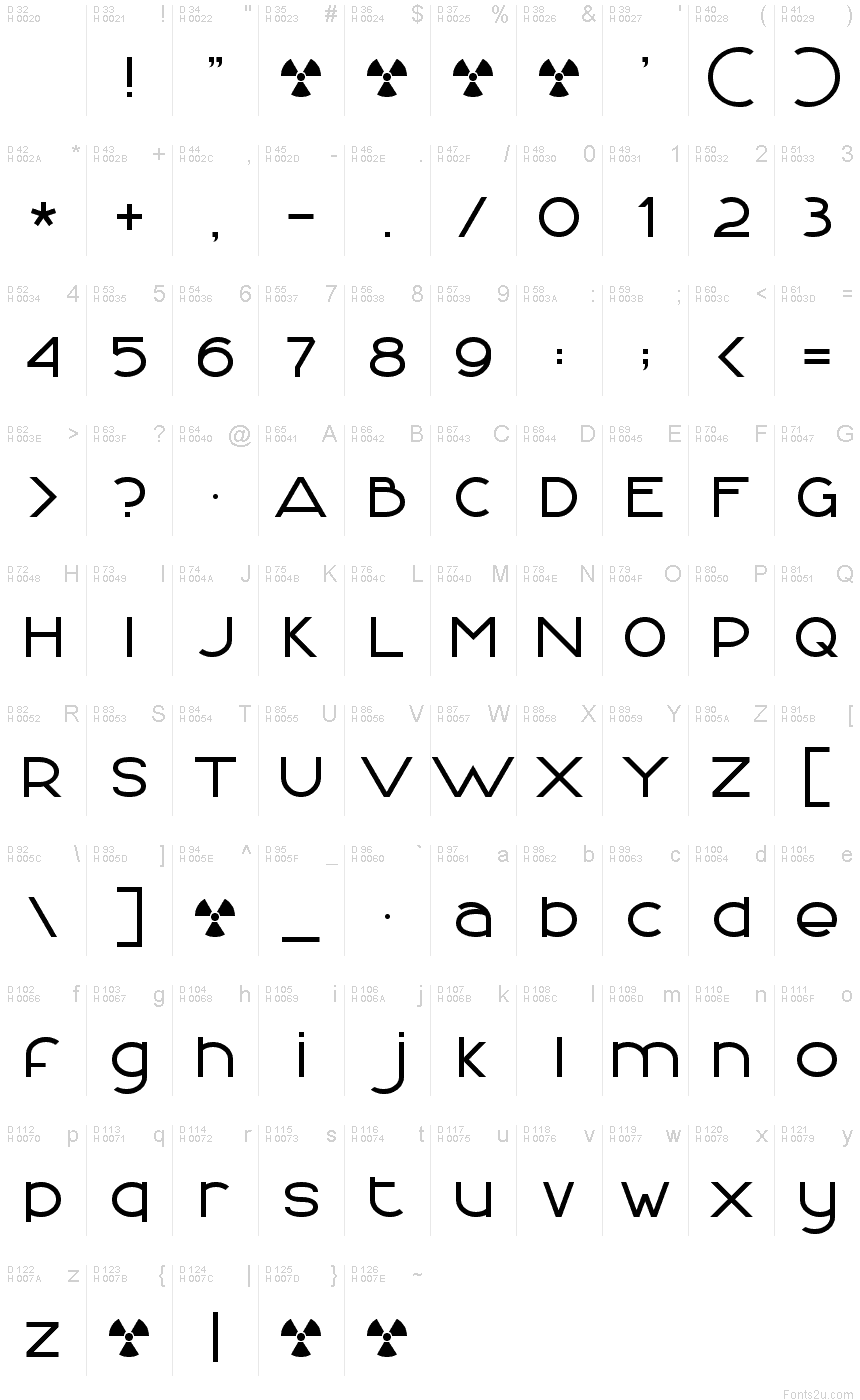
FontLogic autorstwa Stephen.Deken to darmowy, geometryczny krój bezszeryfowy. Czyste, równe kreski i przestronne, koliste kształty nadają mu racjonalny, niemal inżynierski spokój, który ułatwia czytanie na pierwszy rzut oka. Hojne światła wewnętrzne i prosta konstrukcja sprawiają, że litery nie zlewają się, dzięki czemu tekst pozostaje czytelny nawet przy dużej ilości danych lub w mniejszym rozmiarze w gęstych układach.
FontLogic to solidny, bezproblemowy „wół roboczy”, który świetnie sprawdza się w etykietach interfejsów, aplikacjach, dashboardach, infografikach, opakowaniach produktów i minimalistycznym brandingu technologicznym. Ten darmowy font to także naturalny wybór do przejrzystych prezentacji i długich dokumentów, w których przejrzystość jest ważniejsza niż ozdobność. Spróbuj ustawić nagłówki w grubszej odmianie FontLogic, a tekst główny zestawić z prostym krojem humanistycznym, aby zachować spójność systemu bez monotonii.
FontLogic